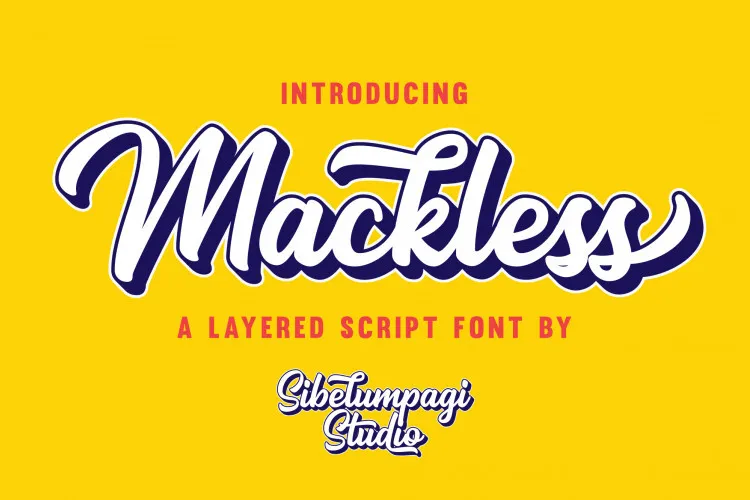
A Mackless Script Font é uma nova tipografia desenhada pela Sibelumpagi Studio. Inspirada em várias técnicas artísticas do design gráfico, esta fonte se tornou um complemento ideal para qualquer projeto que busque um toque de sofisticação clássica. Com sua arquitetura limpa e natural, Mackless Script é uma escolha inteligente tanto para projetos que precisam de um forte equilíbrio tipográfico quanto para aqueles que desejam dar vida a designs inovadores. A fonte incorpora elementos da escrita manual, script de grande porte, script de pincel e logomarcas, proporcionando uma combinação perfeita em qualquer projeto. A Mackless vem com um extra de fontes extruídas para garantir harmonia em projetos exigentes, além de incluir recursos OpenType, como alternativas e ligações. Este é um recurso invaluable aos designers que buscam maior flexibilidade e personalização nas suas criações. Se você está procurando por uma tipografia clássica com uma conotação moderna, a Mackless Script Font pode ser sua escolha perfeita para tornar ainda mais atraentes os seus trabalhos.